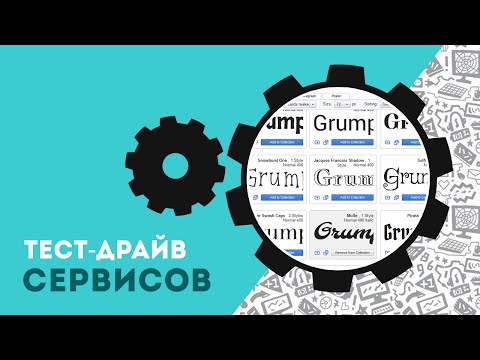
Отличный вариант: шрифты с засечками доступные в Google Fonts
Шрифты с засечками являются элегантным и стильным решением для веб-дизайна. Коллекция Google Fonts предлагает разнообразие таких шрифтов, которые помогут придать вашему проекту уникальность и привлекательность.
Выберите шрифт с засечками, который соответствует характеру и стилю вашего проекта. Учтите, что некоторые шрифты могут быть более формальными, а некоторые - более игривыми и неформальными. Подберите шрифт, который отражает цели и задачи вашего проекта.
Используйте шрифты с засечками для заголовков и выделения основной информации. Они придают тексту солидность и привлекательность, делая его более запоминающимся для пользователя. Но не забывайте умеренно использовать эти шрифты, чтобы не перегрузить дизайн страницы.
Ознакомьтесь со стилевыми возможностями выбранного вами шрифта с засечками. Некоторые из них предлагают различные варианты начертания, жирность и курсивность, что позволяет создавать разнообразные комбинации и подстраивать шрифту под нужные задачи дизайна.